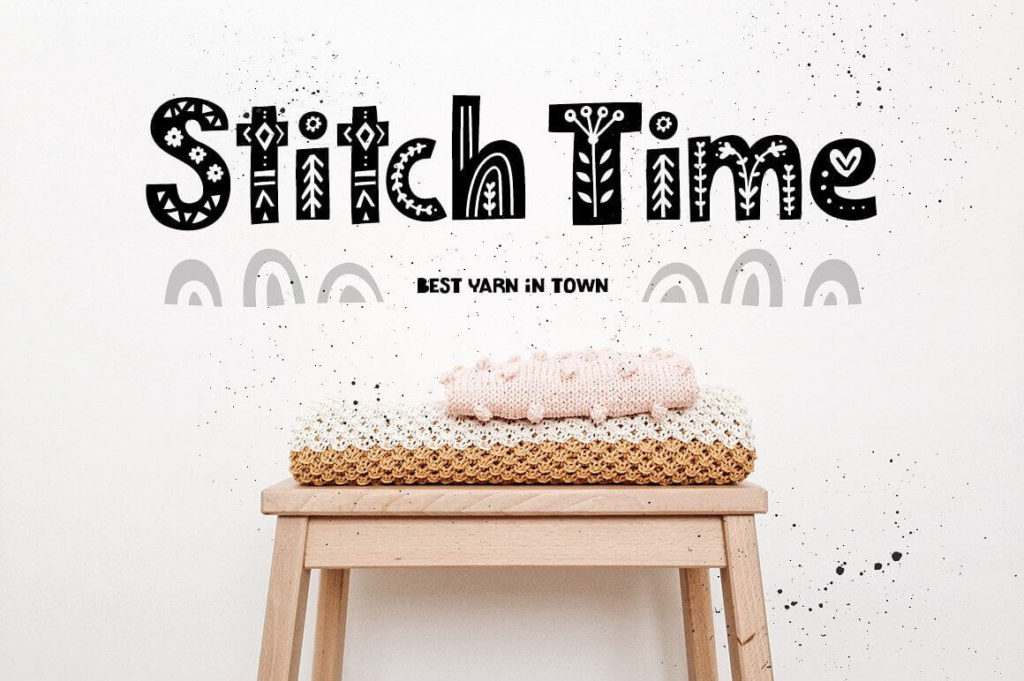
Шрифт Scandinavian Family
Шрифт Scandinavian Family — это игривое декоративное семейство, вдохновлённое скандинавским народным творчеством и минималистичным скандинавским дизайном. Созданный дизайнером Iryna Dviliuk и изданный студией Ira Dvilyuk, шрифт вышел в 2021 году. Каждая буква была тщательно вырезана из бумаги, как детскими руками, что придаёт гарнитуре уникальную текстуру «ручной работы» и тёплый, «детский» характер . Scandinavian Family поддерживает кириллицу, что делает его отличным выбором для проектов на русском языке, где нужен весёлый и неформальный стиль. Оцените его характер, и если вы ищете яркий шрифт для креативных задач, вы можете ознакомиться с ним на этой странице.